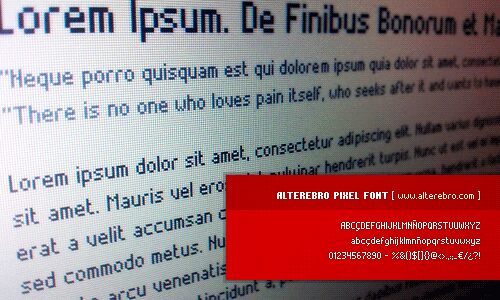
Alterebro Pixel Font, 2009 von Alterebro entworfen, ist eine kostenlose Pixel-Display-Schrift, die aus klaren quadratischen Modulen und treppenförmigen Kurven aufgebaut ist. Ihre schlichten Formen erinnern an frühe Bildschirmbeschriftungen mit niedriger Auflösung.
Sie lässt Text zu einem Teil einer Arcade-Benutzeroberfläche oder eines digitalen Bedienfelds werden, wodurch sie sich gut für Spielegrafiken, Technologieplakate und Artworks für elektronische Musik eignet. Die wiederkehrende Rasterstruktur passt zudem gut zu Pixelillustrationen, einfachen Kachel-Icons und anderen blockbasierten Bildern in Merchandise- oder Event-Grafiken.
Präsentation und Schriftprobe von Alterebro Pixel Font Regular
Zeichentabelle der Schriftart Alterebro Pixel Font Regular
Zeichentabelle von Alterebro Pixel Font Regular: Basis-Lateinisch, Seite 1
Glyphen der Schriftart Alterebro Pixel Font Regular — Basis-Lateinisch, Seite 1